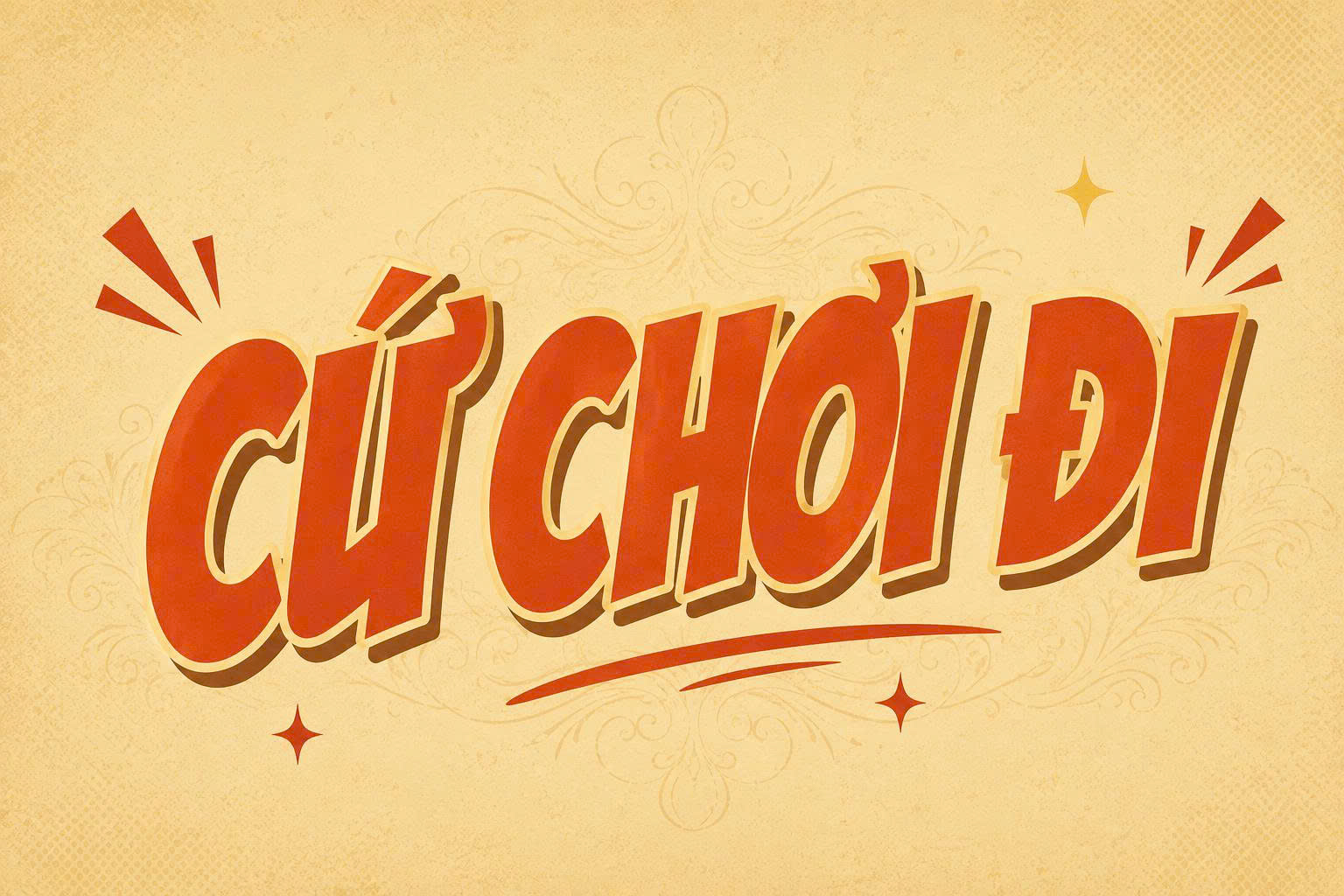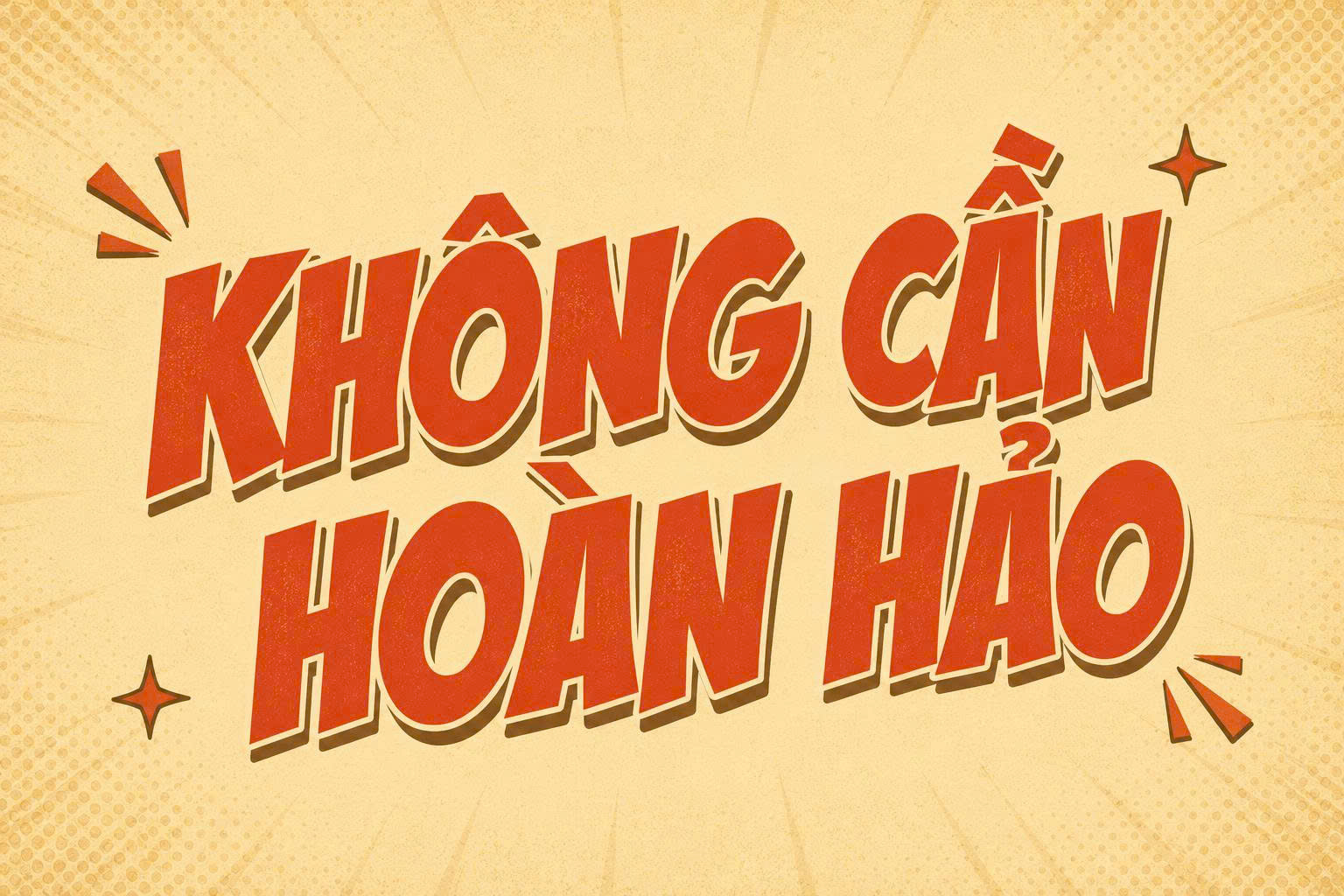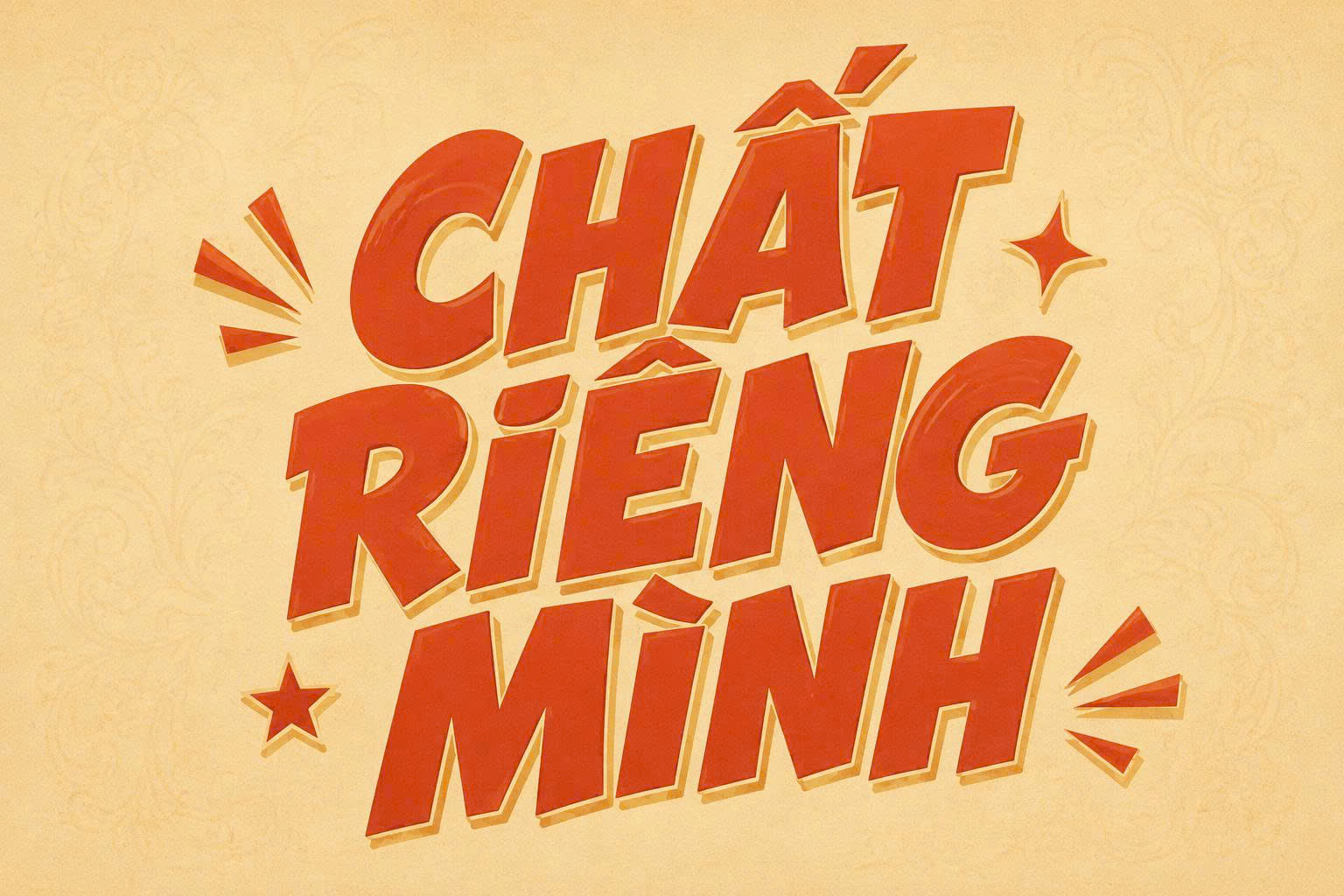
Badaboom font Việt hóa là bộ phông chữ mang phong cách truyện tranh (Comic) kinh điển với những đường nét dày dặn, mập mạp và tràn đầy sự năng động. Được thiết kế ban đầu bởi Blambot, Badaboom đã trở thành lựa chọn hàng đầu cho các dự án cần sự vui nhộn, phá cách và gây ấn tượng mạnh về thị giác. Doozypack.vn chia sẻ link tải font Badaboom Việt hóa chuẩn, hỗ trợ đầy đủ bảng mã tiếng Việt giúp các designer và chủ shop dễ dàng thiết kế bao bì, poster sự kiện mà không lo lỗi dấu hay sai lệch bố cục.
Đặc điểm nổi bật của font chữ Badaboom Việt hóa
Badaboom không chỉ là một phông chữ giải trí thông thường, nó sở hữu những đặc tính thiết kế riêng biệt giúp tạo ra sự bùng nổ cho các nội dung quảng cáo.
Phong cách đồ họa mạnh mẽ và tràn đầy năng lượng
Đặc trưng lớn nhất của font Badaboom Việt hóa là các nét chữ Bold cực dày với độ nghiêng nhẹ, tạo cảm giác như các ký tự đang chuyển động. Phong cách này mô phỏng lại các đoạn hội thoại hoặc hiệu ứng âm thanh (Onomatopoeia) trong truyện tranh siêu anh hùng, mang lại sự phấn khích và trẻ trung cho mọi bản thiết kế.
Cấu trúc chữ in hoa đặc trưng dễ thu hút thị giác
Badaboom chủ yếu sử dụng hệ thống chữ in hoa (All-caps) với các góc bo tròn mềm mại nhưng vẫn giữ được sự chắc chắn. Cấu trúc này giúp tiêu đề của bạn luôn nổi bật, ngay cả khi đặt trên những nền hình ảnh có nhiều chi tiết phức tạp. Khi được Việt hóa tại Doozypack.vn, các dấu thanh được tinh chỉnh mập mạp tương ứng với thân chữ, đảm bảo tính thẩm mỹ đồng nhất.
Ứng dụng của font Badaboom trong thiết kế bao bì và quảng cáo
- Ấn phẩm khuyến mãi: Các từ khóa như “SALE”, “HOT”, “BOOM” khi sử dụng font chữ Badaboom Việt hóa sẽ tạo hiệu ứng bùng nổ, thúc đẩy hành vi mua hàng.
- Sự kiện và Poster: Làm tiêu đề cho các hội chợ, sự kiện dành cho giới trẻ hoặc các thiết kế banner mạng xã hội cần sự phá cách.
- Phối màu sắc rực rỡ: Để tối ưu phong cách Comic, hãy phối font Badaboom với các cặp màu tương phản mạnh như Vàng – Đen, Đỏ – Trắng hoặc Cam – Xanh dương. Hiệu ứng viền (Stroke) đậm quanh chữ cũng sẽ giúp tiêu đề trông “nổi” hơn trên hộp giấy.